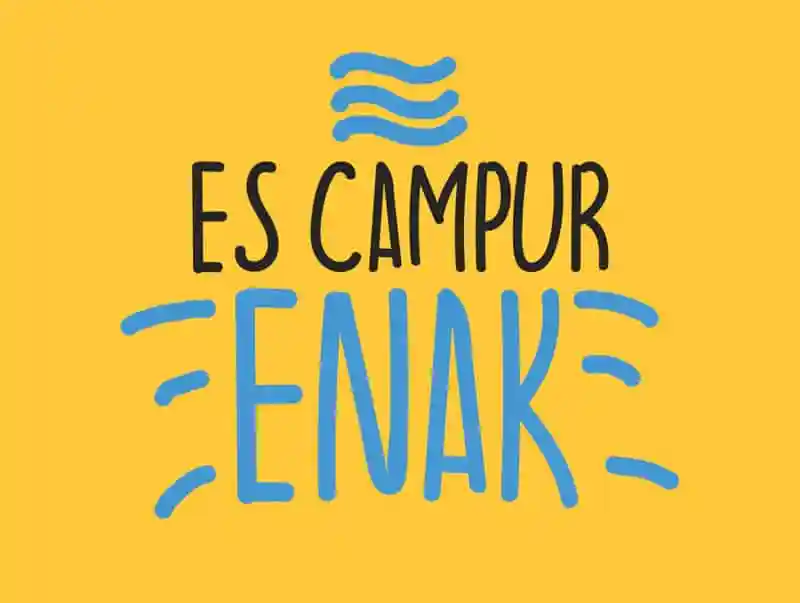
Es Campur Enak Font – Fonte Grátis
Es Campur Enak Font
A Es Campur Enak Font é uma fonte única e atraente criada pelo designer Hamilton, perfeita para adicionar um toque distintivo a qualquer projeto de design. Com linhas finas e elegantes, esta fonte apresenta um caráter moderno e sofisticado que combina facilmente com diversos estilos gráficos. Ideal tanto para uso em títulos quanto em textos mais detalhados, essa fonte oferece uma experiência de leitura agradável sem comprometer o impacto visual desejado. A Es Campur Enak é perfeita para quem busca um estilo diferenciado e elegante que se destaca no meio do design digital. Estamos gratos por qualquer contribuição que você possa fazer, tanto através da compra desta fonte quanto em qualquer outra forma de apoio. Para facilitar a adoção deste projeto, oferecemos uma opção de pagamento por meio do PayPal. Visite o link fornecido para acessar este serviço. Seja qual for sua decisão, estamos certos de que a Es Campur Enak será uma escolha ótima para seu próximo design.